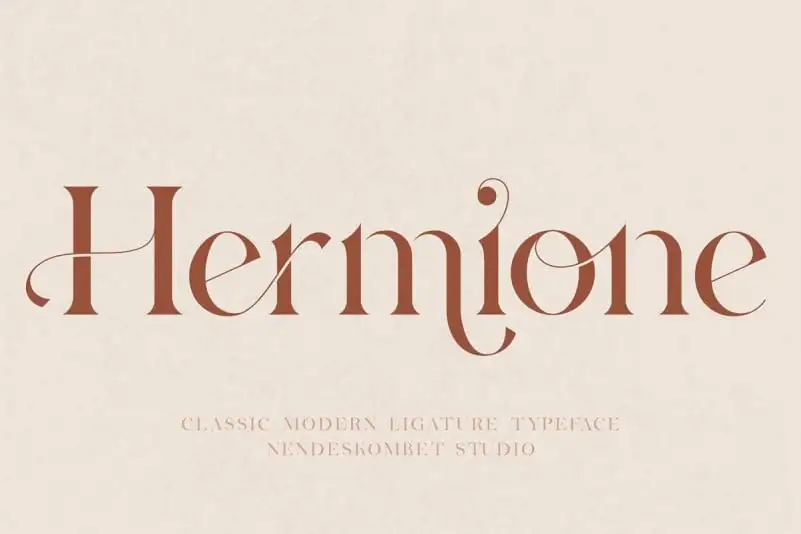
Hermione Serif Font
A Hermione Serif Font é uma elegante serif moderna criada por NendesKombet com uma pitada de ligaturas modernas. Esse tipo de letra perfeito para branding, logotipos e convites, é fácil de ler tanto em grandes fontes como em tamanho mais pequeno. Com 48 ligações, 63 alternativas tanto para letras maiúsculas quanto minúsculas e números/pontuação, Hermione oferece uma versatilidade sem igual. Perfeito para qualquer uso gráfico que você possa imaginar, ela traz ao seu design um charme retro com uma pegada de hoje. Seja você um designer ou editor de texto, a Hermione é uma fonte imperdível para seus projetos.